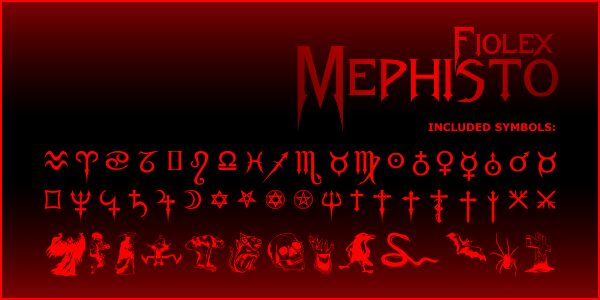
Fiolex Mephisto to darmowy, nowoczesny gotycki font typu display o teatralnym, wysokokontrastowym wyglądzie. Litery balansują pomiędzy dramatyzmem czcionek łamanych (blackletter) a ostrością rodem ze świata mody, łącząc szerokie, masywne elementy z delikatnymi krzywiznami i igłowymi końcówkami, które nadają wielkim literom lekko złowrogiej elegancji.
Doskonale sprawdza się w tytułach na plakatach, okładkach albumów, opakowaniach w stylu „dark romance”, ulotkach eventowych oraz nagłówkach redakcyjnych, gdzie krótki tekst wymaga połączenia surowości z blaskiem. Jako darmowy krój, świetnie nadaje się również do monogramów i kart tytułowych, ponieważ ostre detale i wyrazisty kontrast sprawiają, że nawet kilka znaków nabiera mocnego, emblematycznego charakteru.
Zawiera symbole astrologiczne, tarota i inne motywy mityczne.
Fiolex Mephisto
Includes Astrology, Tarot and other mythical symbols (use the Windows Character Map to insert them).